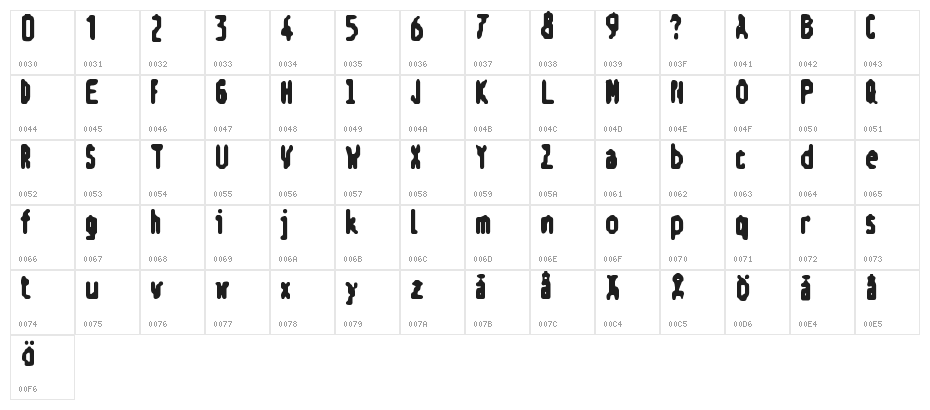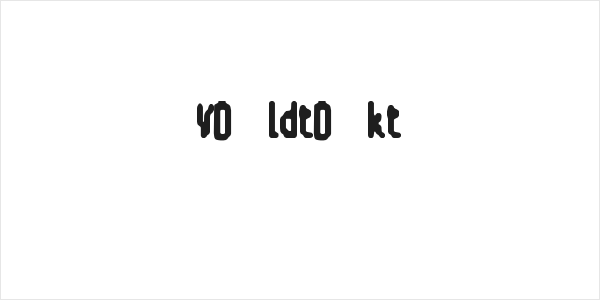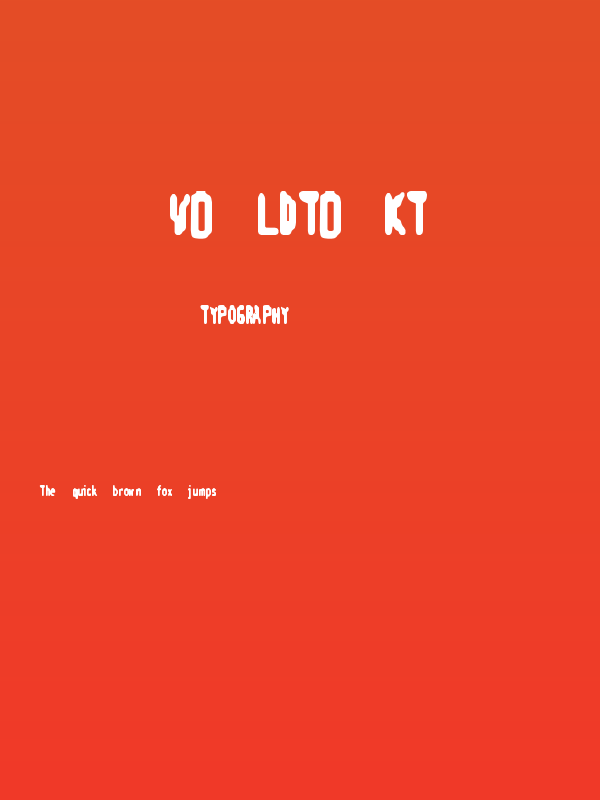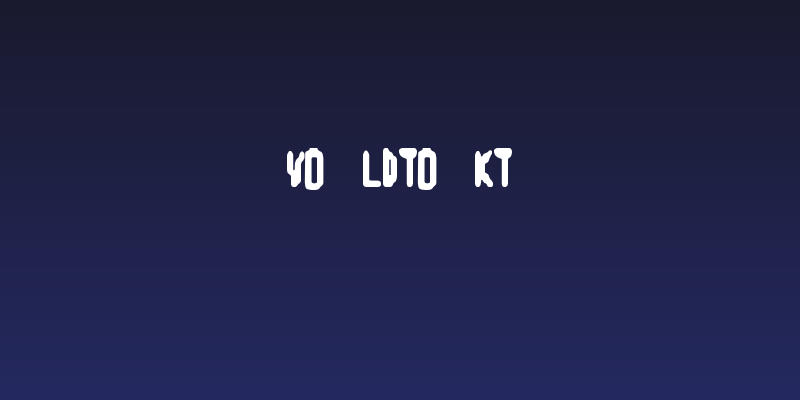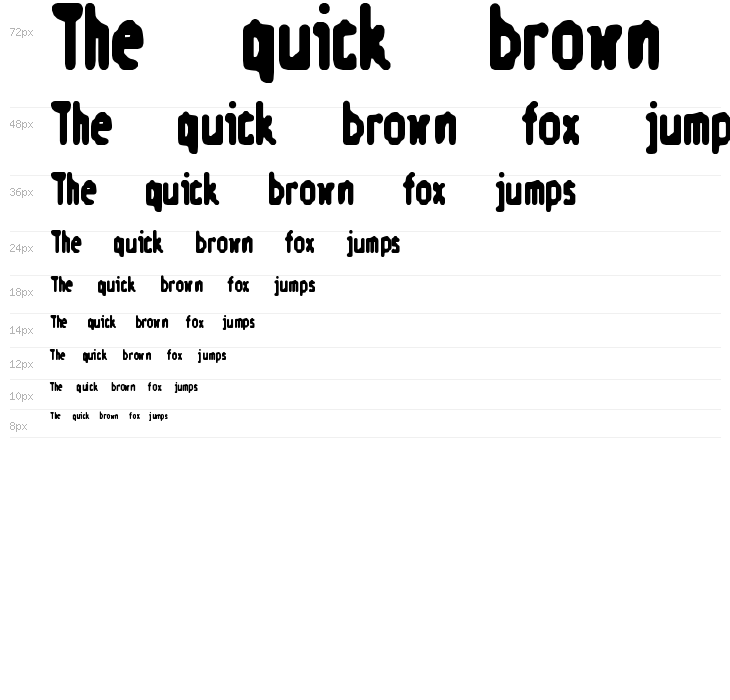
V-ldt-kt Font
| Stile generale | Playful, Creative |
| Progetti proposti | Ideal for children's book covers, playful branding, creative posters, and informal invitations. |